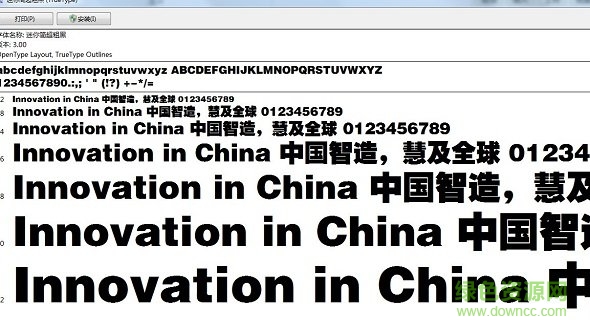
jcacuhei是什么字體?jcacuhei字體是一款渾厚樸拙的迷你簡超粗黑字體,這個字型粗細一律,看上去厚重有力,讓你的字體如行云流水般協調,綠色資源網還有海量特色黑體字體等你下載!
【等線字體】,是繼宋體之后又一重要印刷字體。它與宋體結構相同,但點畫粗壯且粗細一律,起止皆方,氣象豐滿。因其印刷效果似墨團,俗稱黑體!